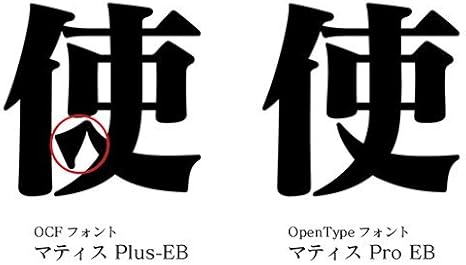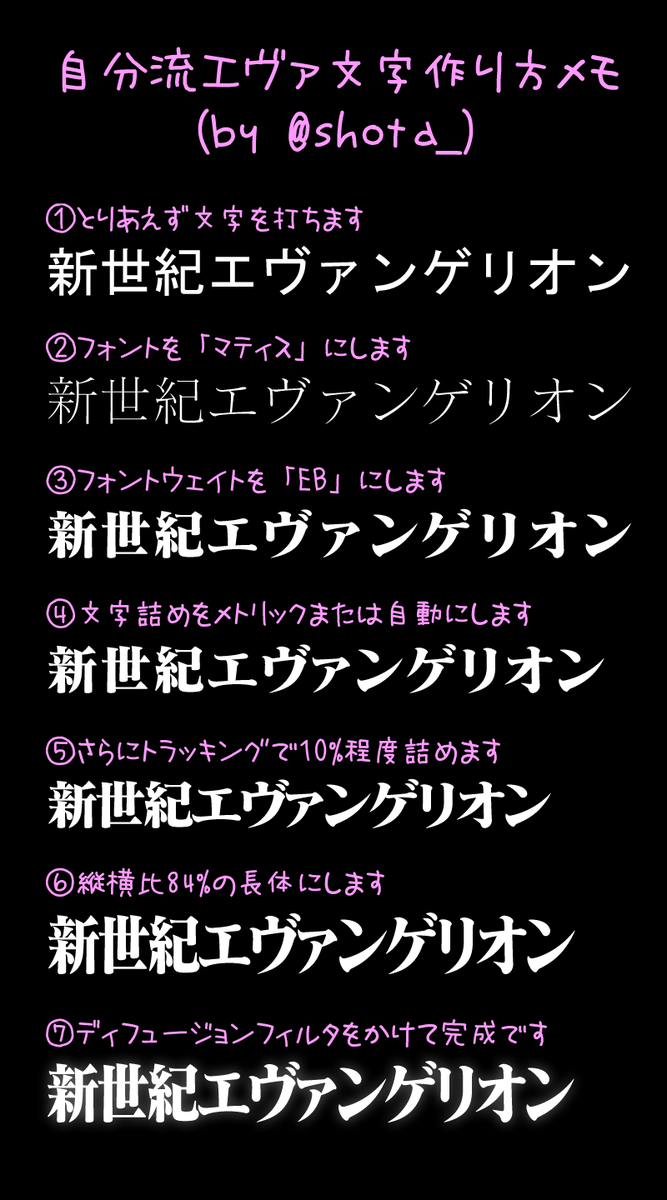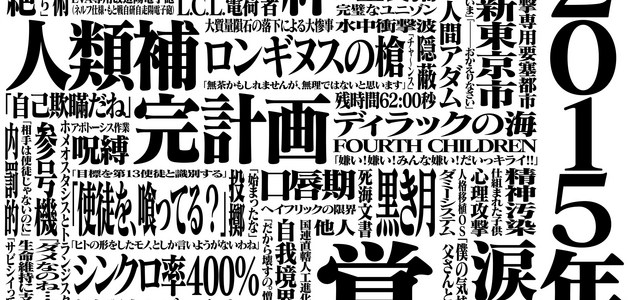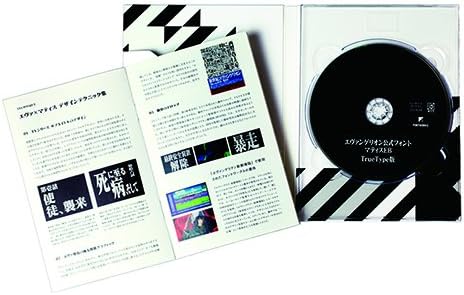
エヴァ 文字 フォント
エヴァ 文字 フォント. エヴァフォントの正体は「マティス Pro EB」¥19,440也 Original Update by 次回 シン・エヴァンゲリオン劇場版 このエヴァフォント、アニメの知名度からしても当然かもしれませんが、すぐ見つけることができました。. エヴァ文字がイラスト付きでわかる! 「新世紀エヴァンゲリオン」にて表示される文字。 「新世紀エヴァンゲリオン」のサブタイトル表示などに現れる明朝体の文字。 「エヴァ明朝」とも通称される。 ちなみにTV版放送当時はフォントワークス社製の「マティスPlus」ファミリー(現在では. Just another site 女の子でも口ヒゲ対策は大事です!.
エヴァ文字がイラスト付きでわかる! 「新世紀エヴァンゲリオン」にて表示される文字。 「新世紀エヴァンゲリオン」のサブタイトル表示などに現れる明朝体の文字。 「エヴァ明朝」とも通称される。 ちなみにTV版放送当時はフォントワークス社製の「マティスPlus」ファミリー(現在では. フォントワークス エヴァンゲリオン公式フォント マティスEB Truetype版発売日:16年11月10日. 『エヴァンゲリオン公式フォント マティスEB TrueType 版』が11月10日にフォントワークスより発売開始! 「新世紀エヴァンゲリオン」で印象的なあの書体“エヴァ明朝”が、PC フォントとして利用可能に!.
フォントワークス エヴァンゲリオン公式フォント マティスEB Truetype版発売日:16年11月10日. エヴァとマティスが共に歩み、互いに進化し続けた年の歴史が分かる“特典ブックレット”が付属。 Chapter2:マティスEB エヴァンゲリオンで行われた文字表現 フォントブログ「エヴァフォントでいろいろ作ってみました」. エヴァとマティスが共に歩み、互いに進化し続けた年の歴史がこの1冊で分かる"特典ブックレット"が、今回の目玉。 エヴァとマティスの出会いの経緯とは? なぜ、庵野監督は、マティスebを選んだのか? エヴァが創ったアニメにおける文字表現とは?.
フォントワークス マティスProEB(エヴァ公式フォント) TV版の各話タイトルはほぼそのままで、劇場版ではフォントの垂直・水平比率や文字間のツメを行っているようです。 追記でご説明のとおり、 フォント制作・販売 フォントワークス 販売価格. Just another site 女の子でも口ヒゲ対策は大事です!. フォントブログ「エヴァフォントでいろいろ作ってみました」 フォントを巡る冒険 第8回近代建築の「叡智」に思いを寄せて ~bake・柿﨑弓子さん 第38回 大阪dtpの勉強部屋 宮地 知 様 ~もっと大阪のデザイン自由度を高くしたい~.